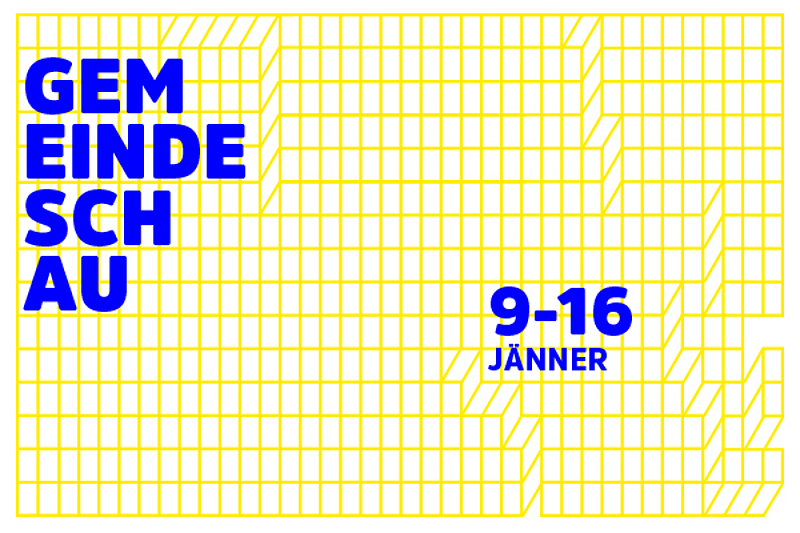
Gemeindeschau – Typografie im Wiener Gemeindebau
Ausstellung, 2016
Grafik Design & Fotografie
Wie jeder Wiener Gemeindebau eine einzigartige Bauweise und dadurch eine unverwechselbare Architektur hat, so hat jedes Gebäude auch einen eigenen Namen und eine dazugehörige Schrift. Studierende der Abteilung Visuelle Kommunikation der Kunstuniversität Linz haben diese Gemeindebauten besucht, die Schriften dokumentiert und schließlich eine digitale Neuauflage geschaffen. Entstanden ist ein Open Repository – ein offenes Archiv von Schriften sowie eine Reihe von Typeface Postern, die mögliche Anwendungsarten zeigen. Die Schriften stehen unter einer Creative Commons Lizenz zum Download und zur Bearbeitung zur Verfügung und werden im Rahmen der Ausstellung Gemeindeschau präsentiert.